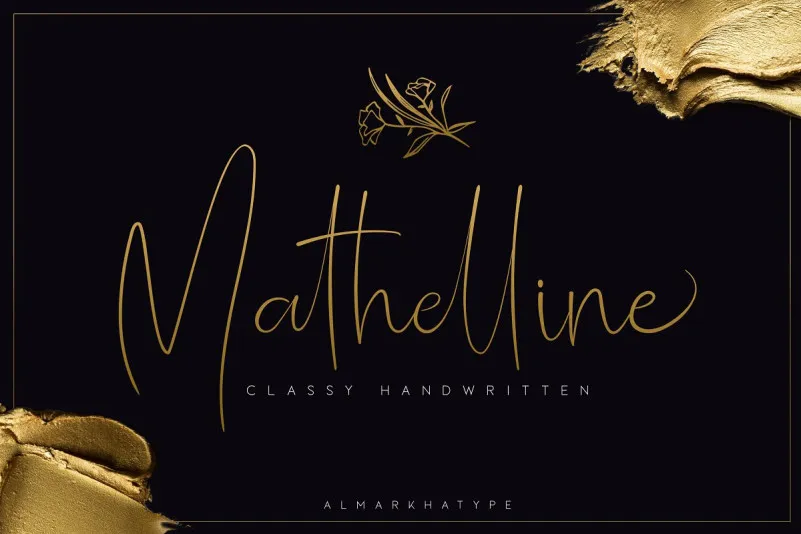
Mathelline Handwritten Font – Download Grátis
Esta é uma fonte script escrita a mão com um aspecto autêntico. É uma fonte escrita a mão moderna que incorpora acréscimos contemporâneos e sofisticados. Ela se destaca perfeitamente para criações de marca, convites e cartas de casamento e até mesmo para rótulos de vinho! Compramos com grande orgulho nosso novo produto Mathelline Font ! É projetada e compartilhada pelo Almarkha Type . A Mathelline Handwritten Font é uma fonte de script elegante, disponível nas versões regular e itálica. Inspirada em luxo e no tipo de mercadoria, esta fonte se destaca como elegante e impressionante em muitas formas para seus projetos atuais. É perfeita para logotipos e criações de marca, fotografia, convites, marcas d’água, anúncios, design de produtos, notas, designs de casamentos, rótulos, embalagens de produto, eventos especiais ou qualquer coisa que precise de um sabor a mão.